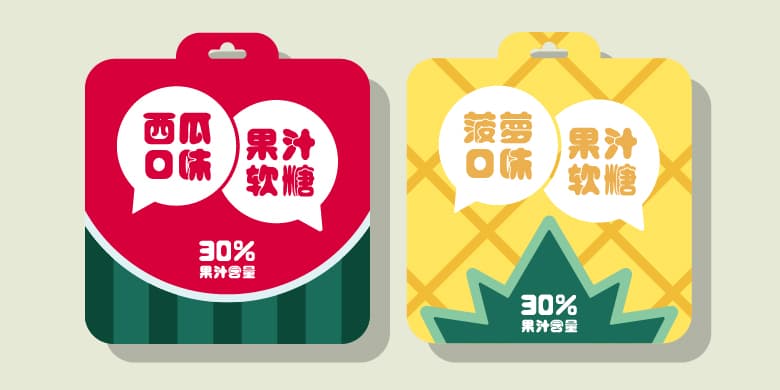
三余肥光体是一款萌胖可爱、柔软慵懒、稚趣十足的卡通类型美术字,字体负空间极小,整体饱满圆润,如同QQ糖/婴儿般柔软且富有弹性的笔划设定,融入部分笔划重叠的特征,营造出萌胖稚趣的氛围。设计之初想把肥光体设计成一款萌胖、柔软、可爱的字体,所以在笔划设定时,加入圆润粗厚的笔画特点,通过控制曲线线条的张力弧度,压缩字面负空间,部分笔划做重叠处理,在易识别的情况下,笔画间的灵活搭配更突显字体的柔软稚趣。 适用于海报招贴,漫画绘本、包装产品等周边领域。